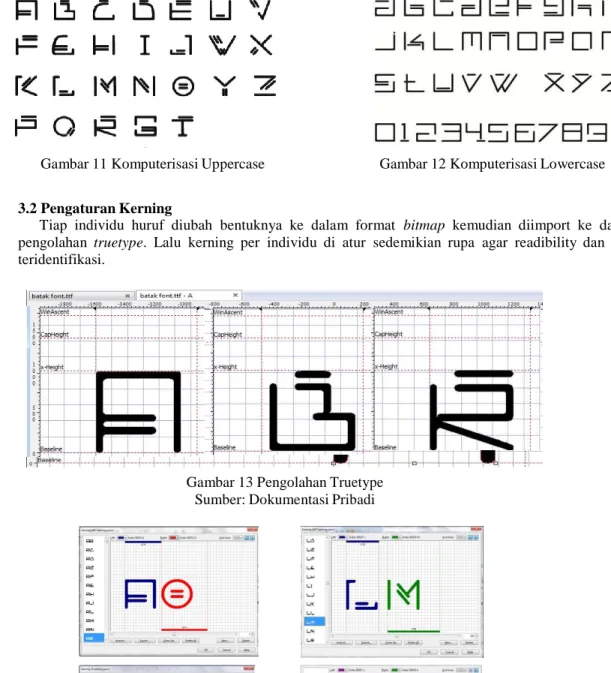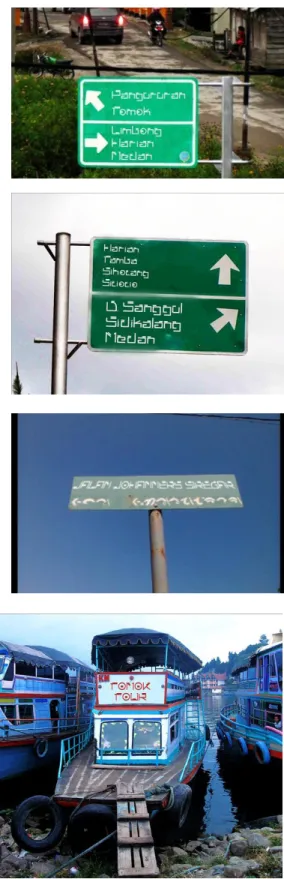
PERANCANGAN TYPEFACE BERBASIS AKSARA BATAK TOBA
Abstrak
Aksara Batak Toba merupakan warisan budaya luhur suku Batak yang mendiami daerah Tapanuli. Dari lima jenis suku Batak yang ada masing-masing memiliki aksara sesuai tempat penggunaannya.
Penggunaan aksara ini tidak lagi efektif pada masa kini karena huruf latin lebih dominan dan efisien digunakan dalam berkomunikasi. Dahulu kala aksara kebanyakan digunakan para datu sebagai pemimpin upacara adat namun seiring perkembangan waktu pengguna aksara tidak sebanyak dahulu. Aksara menjadi jarang digunakan dan mulai terlupakan karena sifat aplikatifnya yang terbatas di masa kini.
Dengan demikian aksara ini membutuhkan perhatian khusus agar aksara ini tetap memiliki tempat dalam tatanan nilai budaya Batak Toba. Ide ini kemudian dikembangkan menjadi sebuah konsep rancang visual typeface berbasis aksara Batak Toba yang memiliki karakter anatomi dan proses konstruksi pembuatannya didasarkan pada kaidah-kaidah dalam tipografi, sehingga adaptasi ini muncul dalam rupa font latin. Dari bentuk aksara silabis (suku kata) menjadi fonetik (huruf tunggal) aplikasinya sebagai font di komputer. Setelah penelitian dan perancangan, kemudian typeface yang siap pakai ini disosialisasikan di area lokal, diprioritaskan pada tingkat pendidikan dan pemerintahan, yang pada penggunaannya untuk kepentingan headline.
Abstract
Batak Toba script is a noble cultural heritage of Batak tribes from Tapanuli. However those scripts are no longer effective and effiecient. In ancient times the scripts are mostly used by the datu as a ceremonial leader, but as the time passes the user scripts are not as much as previously. Script have been rarely used and began to be forgotten because of the limited use at present. Thus this script requires special attention that this script still has cultural value system of Batak Toba. This idea was later developed into a visual design concept of Batak Toba typeface based on it scripts character of anatomy and construction process of manufacture based on the rules of typography, so it appears in the form of adaptation latin fonts. From the shape of the syllabic script into phonetic application as a font in computer. After research and design process then this typeface is ready to socialized to local people with schools are for education as knowledge about revitalitation Batak Script into latin alphabet and government level which its use for the headlines text.
1. Pendahuluan
Budaya nusantara tampak abstrak eksistensinya di era globalisasi saat ini, perkembangannyapun tampak melambat dan mengalami penurunan. Oleh sebab itu diperlukan sebuah terobosan untuk menggali kembali dan menegakkan budaya nusantara yang kaya akan nilai luhur secara filosofis dan kaya akan estetika secara visual.
Sehingga budaya ini mendapatkan posisi di hati masyarakat.
Aksara nusantara adalah salah satu warisan yang layak untuk dilestarikan, beragam jenis aksara yang beredar di nusantara merupakan turunan dari akar Palawa, yaitu : Aksara Ha-na-ca-ra-ka, Surat Ulu, Surat Batak, Aksara Sulawesi, dan Aksara Filipina.
Dari kelima aksara ini Aksara Jawa (Ha-na-ca-raka) merupakan aksara yang paling dikenal masyarakat karena sumber referensi buku dan informasi yang memadai. Berbeda dengan Aksara/ Surat Batak masih sangat membutuhkan perhatian khusus, generasi muda Batak bahkan sebagian tidak mengetahui adanya aksara ini.
Faktor penyebab aksara batak tidak memiliki tempat dibenak masyarakat adalah:
• Sastra batak banyak dituangkan dalam wujud tulisan hanya pada zaman dahulu sebelum para zending (misionaris) datang ke tanah batak.
• Falsafah, turi-turian, dan umpasa disebarkan secara lisan dari mulut ke mulut
• Masuknya aliran agama membuat aksara batak (pustaha) terancam punah dan sebagian dimusnahkan karena dianggap benda najis, karena pustaha ditulis oleh datu (dukun)
• Sisa pustaha yang ada kini berada di museum Belanda dan Jerman.
• Akhir-akhir ini sekitar akhir tahun 2000-an aksara Batak jarang diajarkan di sekolah-sekolah di Samosir.
Gambar 1 Silsilah Aksara Nusantara Sumber: Kozok, 2014
Apabila dilihat dari sisi efektivitas dan efisiensinya maka aksara batak sangat jauh dibawah huruf latin.
Penulisannya yang cukup rumit dan karena berupa silabis (suku kata) bukan fonetik (tunggal) jenis aksara berupa lambang fonem (a-b-c-d-e). Apabila zaman dahulu masih efektif digunakan sebagai alat komunikasi namun saat ini dinilai kurang efektif. Oleh sebab itu perlu dilakukan sebuah upaya agar aksara batak toba tetap ada dan menjadi identitas suku batak toba itu sendiri.
Salah satu cara adalah dengan mengadaptasi karakter, personaliti, dan sifat aksara batak itu sendiri ke dalam bentuk huruf latin. Revitalisasi ini bertujuan sebagai entry point untuk memperkenalkan aksara batak kepada masyarakat lokal (samosir) bahkan masyarakat luas. Revitalisasi ini pada akhirnya diharapkan dapat digunakan sebagai typeface untuk berbagai kebutuhan dan disebarkan dengan memanfaatkan media offline dan online sehingga dapat diakses dengan mudah.
Dengan demikian maka untuk merancang typeface secara baik dan benar menurut secara aturan tipografi maka revitalisasi ini dikonstruksi sesuai dengan kaidah-kaidah ang berlaku dalam tipografi.
2. Landasan Teori
Tahap awal yang digunakan adalah dengan mengamati dan meneliti dari sisi visual dan teknis penulisan dan teknis pembacaan aksara Batak Toba. Bentuk dan proporsi aksara batak tampak berat dan pendek akibat bahan tinta (getah dan arang) yang digunakan ‘meleber’ memenuhi sekitar ruang negatif aksara, selain itu juga anatomi huruf menjadi terganggu karena tidak adanya aturan yang pasti untuk menulis aksara batak toba. Sehingga para datu yang senang berkelana dari satu daerah ke daerah lain terpengaruh tempat yang ia singgahi, demikianlah setiap pustaha memiliki karakter aksara yang berbeda menurut tangan penulis (datu). (Haswanto, 2001)
Gambar 2 Aksara Batak Sumber: Kozok, 2014 2.1 Proposi dan Karakter Visual
Referensi visual di bawah ini tampak sangat berbeda antara konstruksi proporsi huruf latin dengan aksara batak pada pustaha Beloit.
Gambar 3 Proporsi Huruf Latin Sumber Perkins
Kesan umum yang dimunculkan oleh huruf latin berdasarkan pengamatan langsung adalah;
1. Huruf tampak proporsional dan simetris 2. Bentuk huruf berdasarkan bentuk geometri,
kotak, dan lingkaran
3. Mempunyai ketebalan dan ketipisan yang kontras
4. Huruf tampak dinamis
5. Terdiri dari bidang horisontal dan vertikal 6. Jika dijadikan sebuah kalimat tiap huruf
tampak menyatu atau 7. match.
Gambar 4 Pustaha Beloit Sumber
Sedangkan pada aksara Batak Toba memunculkan kesan visual, seperti;
1. Tiap aksara memiliki kesan melebar sehingga tampak pendek atau ‘gepeng’
2. Memiliki ketebalan atau stroke yang konstan 3. Tiap aksara mengandung kesan lengkung 4. Tampak garis ganda di bagian atas ascender
5. Aksara tampak memiliki ruang (ground) terbuka dari kedua ujung 6. Tidak tampak susunan atau jarak ‘spasi’
Terbuka
Gambar 5 Ruang Terbuka pada Aksara Batak Toba Sumber: Dokumentasi Pribadi
2.1 Analisa Anatomi Huruf Baseline, Capline, Meanline
Dalam aturan perancangan huruf dalam tipografi dikenal ketiga istilah di atas yang masing – masing memiliki fungsi sebagai garis horisontal penentu yang jika ditarik dari sudutnya maka akan membentuk garis maya sebagai pola anatomi huruf latin. Dalam pustaha batak beloit garis maya ini sangat bervariasi dan tidak mutlak sifatnya sehingga tiap aksara tampak varian bentuknya dan tidak memiliki garis vertikal yang memudahkan membaca mengenali karakter dan membaca pustaha. Tidak ditemukan garis utama yang menghubungkan huruf secara individu, seperti aksara Jawa atau India. Padahal aksara batak toba tidak mengenal huruf kapital, kecil dan spasi. Bentuk/ struktur yang tidak simetris ini disebabkan oleh penulisan aksara secara vertikal dari bawah ke atas namun di baca secara horison dari kiri ke kanan.
Ascender, x-height, descender
Garis vertikal penyusun individu huruf ini membantu titik temu garis maya menjadi simetris sehingga antar huruf, antar kata, dan antar baris mudah diidentifikasi. (Sihombing, 2001). Sedangkan di dalam aksara Batak Toba, tidak tampak sama sekali garis maya ini dan hal ini mempersulit aksara tersebut untuk dibaca.
2.2 Konstruksi Huruf
Dari hasil analisa anatomi maka elemen garis pembentuk aksara batak seperti tabel berikut:
Tabel 1 Analisa Konstruksi Huruf Sumber: Dokumentasi Pribadi
KELOMPOK BENTUK HURUF LATIN AKSARA BATAK TOBA
Garis tegak -datar
21 4 (ma,ta,pa,ja)
20 0
Garis tegak-miring
9 4 (a,ha,ja,da)
11 5 (ta,da,ja,nga,nya)
Garis tegak - lengkung
3 4 (a,ha,ra,ga)
6 2 (sa,la)
Garis lengkung
0 6 (a,ha,ra,ba,wa,ya)
2 3 (a,ma,ba,ya)
2 2 (na,ba)
Jika dilihat dari perbandingan jumlah tiap bentuk garis maka dapat disimpulkan bahwa aksara batak toba memiliki gabungan unsur garis-garis ini dalam tiap individu huruf. Jelas sekali jumlah terbanyak adalah garis lengkung sebanyak 6 aksara sedangkan garis tegak lurus o pada aksara batak toba namun berjumlah 20 pada huruf latin.
2.3 Pola Huruf
Setelah dipertimbangkan maka bentuk yang akan digunakan adalah penggabungan tiap unsur garis membentuk individu latin berkarakter aksara batak toba yang mana kebanyakan berbentuk gepeng menjadi lebih tegak. Dengan basis pustaha Beloit yang tampak halus, kurus dan lebih slim.
Gambar 6 Pola Dasar Sumber: Dokumentasi Pribadi
Gambar 7 Pola Final Komputer Sumber: Dokumentasi Pribadi
3. Desain Sketsa
Beberapa alternatif yang dibuat berdasarkan penelitian dan analisa menjadi pedoman untuk menciptakan huruf latin yang berkarakter aksara batak toba, kemudian hasil sketsa akhir dikomputerisasi hingga ke dalam bentuk truetype.
Gambar 8 Sketsa Sumber: Dokumentasi Pribadi
2.4 Sketsa Final & Komputerisasi
Gambar 9 Sketsa Final Uppercase Sumber: Dokumentasi Pribadi
Gambar 10 Sketsa Final Lowercase Sumber: Dokumentasi Pribadi
Gambar 14 Pengat uran Kerning
Gambar 11 Komputerisasi Uppercase Gambar 12 Komputerisasi Lowercase
3.2 Pengaturan Kerning
Tiap individu huruf diubah bentuknya ke dalam format bitmap kemudian diimport ke dalam software pengolahan truetype. Lalu kerning per individu di atur sedemikian rupa agar readibility dan legibility nya teridentifikasi.
Gambar 13 Pengolahan Truetype Sumber: Dokumentasi Pribadi
3.3 Hasil Desain
Hasil proses penelitian, analisa, dan perancangan typeface berkarakter kasara batak ini menghasilkan 2 set character font, yaitu :
• Set Character Regular (Kompatibel di semua software)
• Set Character Italic (Hanya dapat digunakan di Adobe dan Microsoft)
Uppercase font digunakan sebagai display headline atau judul karena tingkat keterbacaannya lebih mendukung dibandingkan lowercase yang terlalu lemah untuk diidentifikasi apabila digunakan sebagai bodytext. Font ini diberi nama Surat Toba, sesuai dengan asalnya yaitu Toba, sedangkan surat dalam bahasa batak berarti tulis.
3 Aplikasi Desain Huruf
Uji coba huruf di bawah ini menggunakan beberapa Placement text seperti (sign system) di Samosir dengan Uppercase tampak lebih jelas dan mudah diidentifikasi tiap individu huruf, sedangkan lowercase tampak kurang jelas. Maka diputuskan bahwa typeface ini digunakan hanya untuk Headline atau Judul, bukan untuk bodytext.
Gambar 15 Placement Text Sumber: Dokumen Pribadi
5. Penutup
Demikianlah proses penelitian dan perancangan typeface berbasis aksara Batak Toba ini dibuat dengan pengumpulan data serta referensi studi pustaka yang memadai. Dengan arahan dan bimbingan dari berbagai pihak sehingga menambah wawasan penulis mengenai budaya Batak Toba bertambah luas lagi. Tujuan desain huruf ini kembali pada rumusan masalah dan pemecahannya, semoga dapat difungsikan sebagaimana mestinya baik oleh segmentasi desainer ataupun orang yang membutuhkannya sebagai bahan pembelajaran dalam khazanah budaya Batak Toba. Namun begitu hasil perancangan ini tetap membutuhkan banyak perbaikan dan penyempurnaan baik dari aspek bentuk, komposisi, dan konstruksi, juga teknis secara komputerisasi. Karena typeface ini secara readibility dan legibility sangat mungkin digunakan sebagai headline, namun untuk bodytext masih membutuhkan eksplorasi lagi.
Daftar Pustaka
[1] Sihombing, Danton. 2001. Tipografi Dalam Desain Grafis, KPG, Jakarta.